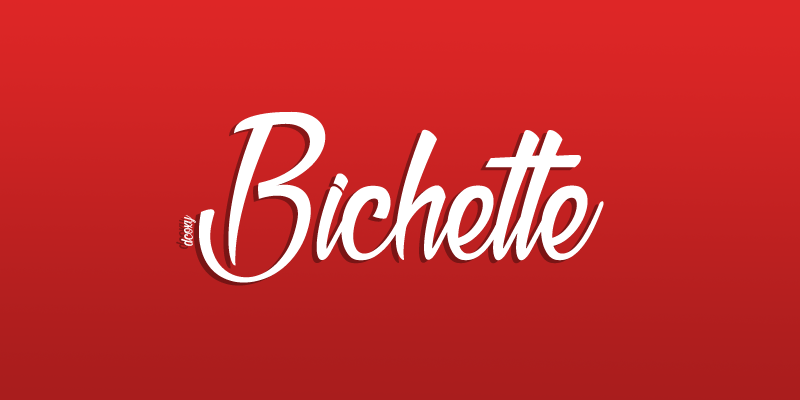
Bichette Font – Fonte Grátis
Bichette Font
A Bichette Font é uma encantadora fonte feita à mão criada por Hamilton. Essa elegante fonte transmite um ar descontraído e carregado de personalidade, perfeita para aplicativos como cartões de visita, anúncios digitais ou design gráfico pessoal. Com linhas suaves e traços delicados que remetem à escrita a mão, a Bichette é ideal para quem busca uma fonte única e autêntica. Seu estilo único encaixa-se perfeitamente em ambientes de comunicação visual contemporâneos, seja ela usada no design digital ou impresso. Quer incorporar essa fonte charmosa aos seus projetos? Para uso comercial ou promocional, você precisará de uma licença. Entre em contato conosco antes:  Eles estão à disposição para fornecer mais informações sobre o processo de aquisição e usar os recursos que a Bichette tem a oferecer. Adquira a sua cópia exclusiva da Bichette Font e faça seu design se destacar entre a multidão. Através da simplicidade, Hamilton criou uma fonte marcante e versátil, que você certamente irá adorar usar no seu próximo projeto.